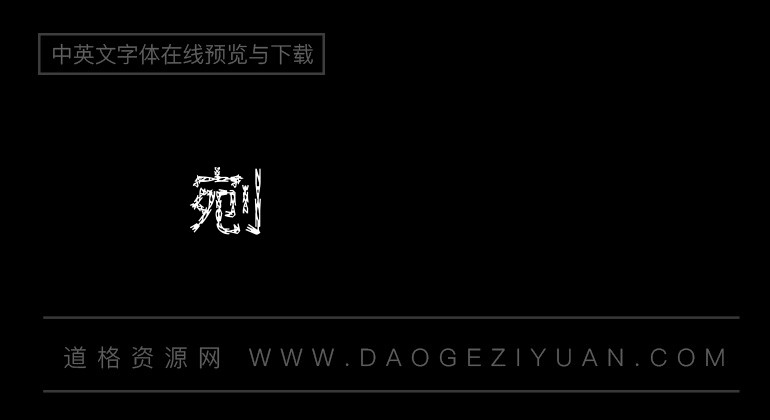
金梅公司名字范例字体
金梅公司名字范例字体是一款由金梅公司开发的一款字体,它具有优美的曲线线条,清晰的字形,细腻的笔画,清新的风格,让文字更加精致,更具有视觉冲击力。此外,它还具有良好的可读性,可以让文字更加清晰、易读、易记,从而让文字更加精致。此外,这款字体还具有优秀的可扩展性,可以根据不同的使用场景,自由调整字体的大小和粗细,从而更好地满足用户的需求。
金梅公司名字范例字体是一款非常不错的手写艺术字体,具有很好的视觉感,适合于文化类的宣传设计、商业类品牌的广告和产品包装设计以及个性化文字排版等较多场景。